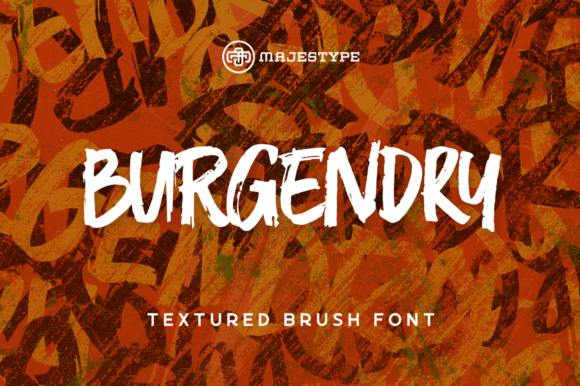
Creativefabrica Burgendry Font 2021
[Creativefabrica] Burgendry Font (2021)
Burgendry - это крутой и матовый дисплейный шрифт.
Независимо от темы, этот шрифт станет отличным дополнением к вашей библиотеке шрифтов, поскольку он способен возвысить любое творение.